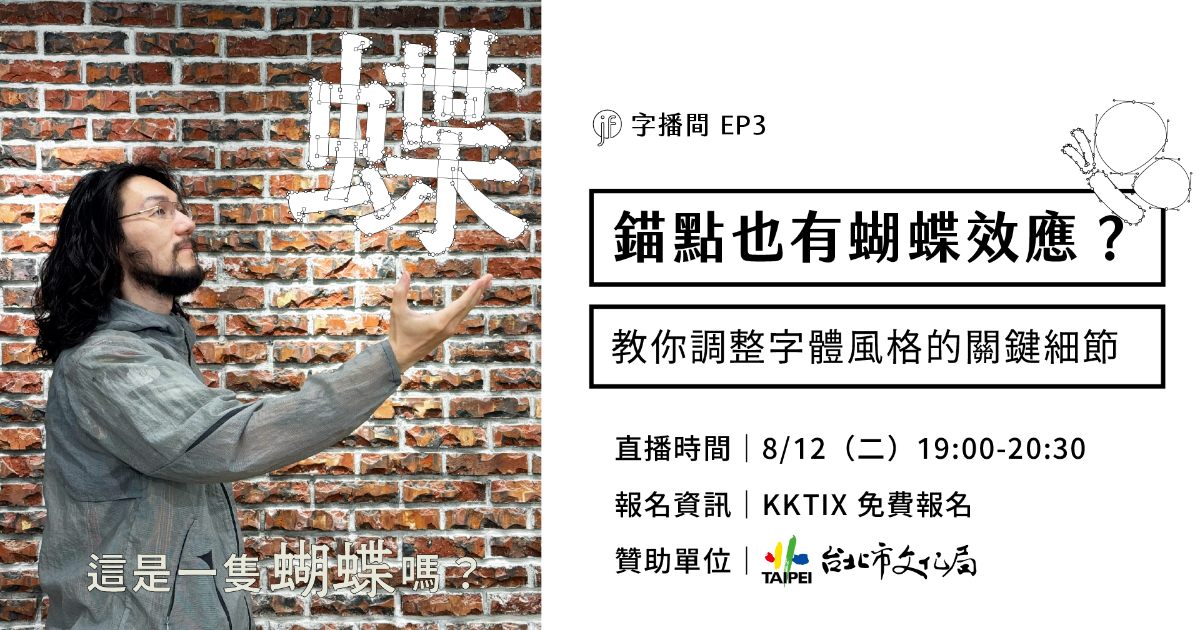
正在開發新字型的國庭,從 EP1 以來的兩個月之間,做了許多風格嘗試
圓一點、瘦一點、軟一點、有腰身⋯⋯
有了基本骨架和筆形後,風格切換其實不用打掉重練
只要熟悉錨點觀念就可以!
🦋 如果你有以下症頭
想要用既有字體當基底做標準字,但是不知道怎麼做出特色🫠
客戶一直說想要更軟一點圓一點尖一點,到底什麼意思🤯
字體市場風格好滿,我是不是沒有發揮空間了😢
每次改一個錨點,整個字都會 tsáu-tsing khì,真的好痛苦😭
本集國庭將教你牽一髮動全身的錨點技巧
讓你不用從零開始,就可以創造各種造型